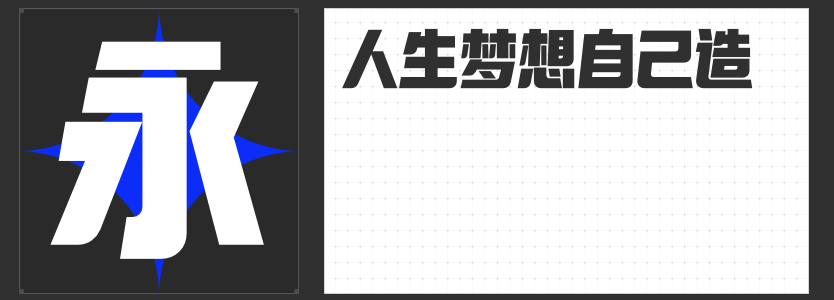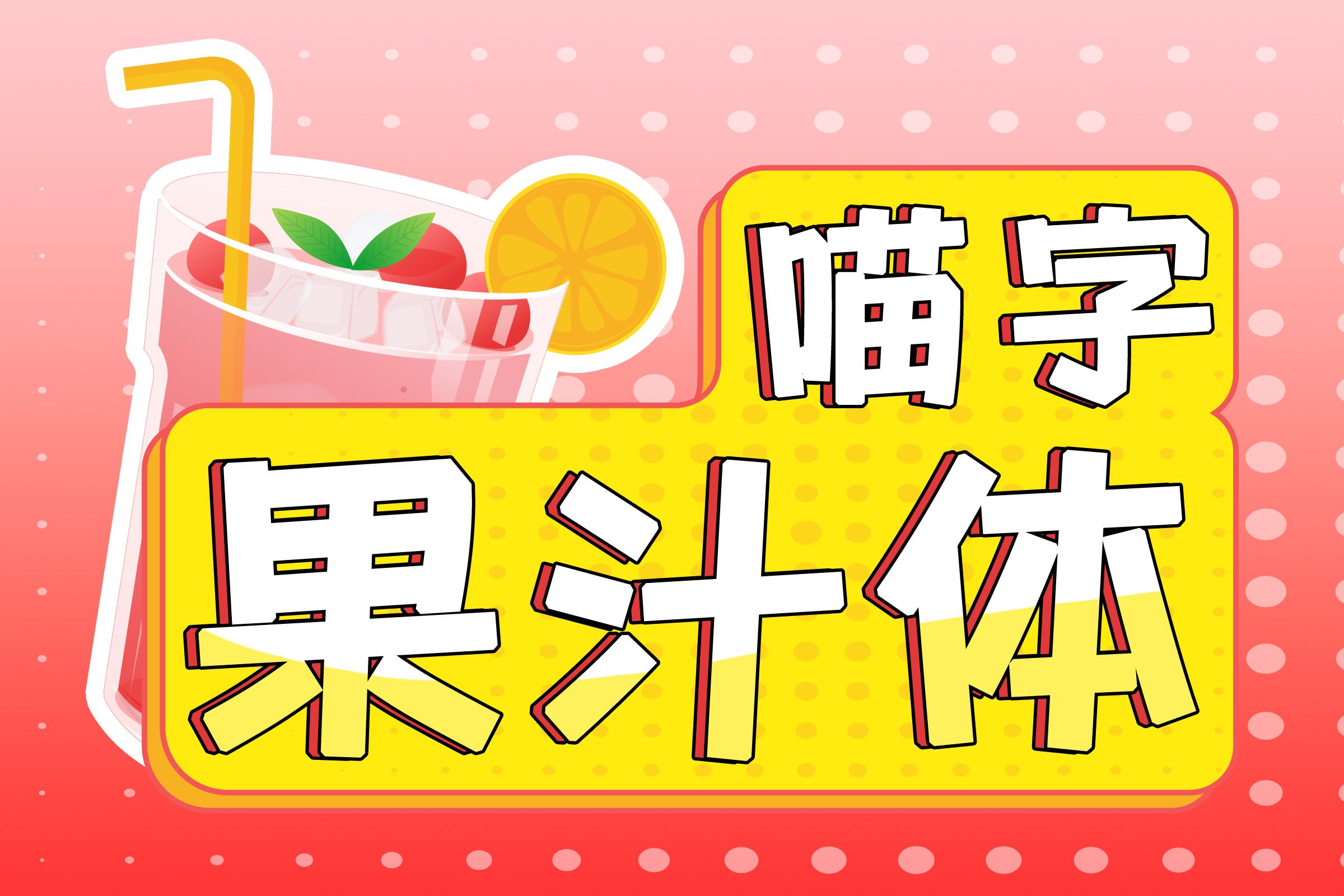
创意无界:四款点亮广告设计的字体精灵🧚
在广告设计的视觉战场上,字体不仅是信息载体,更是传递品牌性格的视觉符号。以下四款创意字体如同四位性格迥异的“视觉艺术家”,以独特魅力为设计注入灵魂。
一、励字圆梦简 常规
这款字体以直线为骨,圆弧为韵,恰似圆规与直尺共舞。其笔画转折处柔和的圆弧处理,既保留了黑体的现代感,又注入圆体的亲和力。中宫松散的结构让文字呼吸感极强,适合高端品牌广告中传递温暖而不失专业的气质。当需要表现母婴产品、健康行业或文化类项目的温柔力量时,它能让标题瞬间化作春风。
二、励字志向黑简 特粗
将黑体的稳重与圆体的流畅熔铸一体,励字志向黑简 特粗在直角转折处增添外圆角设计,如同给钢铁注入液态水银。超粗笔画带来的视觉冲击与圆润细节形成巧妙制衡,尤其适合需要强调力量感的科技产品、运动品牌或活动主视觉。其饱满的字面在LED屏显中依然清晰锐利,是数字时代难得的“屏显艺术家”。
三、励字造梦简 超粗
这款字体用圆润的笔画构建出童话世界般的视觉空间。超粗笔画与留白区域的呼吸式排版,让文字既憨态可掬又充满现代设计感。转角处夸张的圆弧处理,仿佛给每个字母戴上可爱的“安全帽”,尤其适合年轻化品牌、儿童产品或是需要打破严肃感的创意海报。其萌系基因能让观众瞬间卸下心防。
四、喵字果汁体
设计灵感源于饮品吸管的创意,让这款字体自带“可饮用”属性。笔画中流动的线条感与半透明质感,如同吸管中摇曳的果汁,为饮料包装、菜单设计注入鲜活趣味。其半封闭笔画的镂空处理,既现代又充满解构主义美感,特别适合表现夏日饮品、轻食品牌或需要强化味觉联想的场景。
这四款字体如同设计师的“视觉调色盘”,它们不仅突破传统字体的功能边界,更以设计智慧赋予广告更深层的情感联结。当创意需要突破常规时,不妨让这些字体精灵为你的设计注入奇妙化学反应。